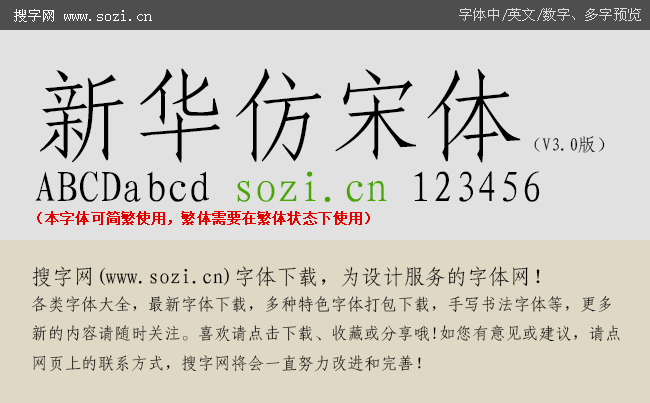
新華仿宋體
搜字網(wǎng)提供一款新華仿宋體字體下載,仿宋字體是印刷字體的一種,仿照宋版書(shū)上所刻的字體,筆畫(huà)粗細(xì)均勻,粗細(xì)一致、秀麗狹長(zhǎng),適用于樣本畫(huà)冊(cè),報(bào)紙排版,網(wǎng)頁(yè)設(shè)計(jì)等廣告設(shè)計(jì)應(yīng)用。